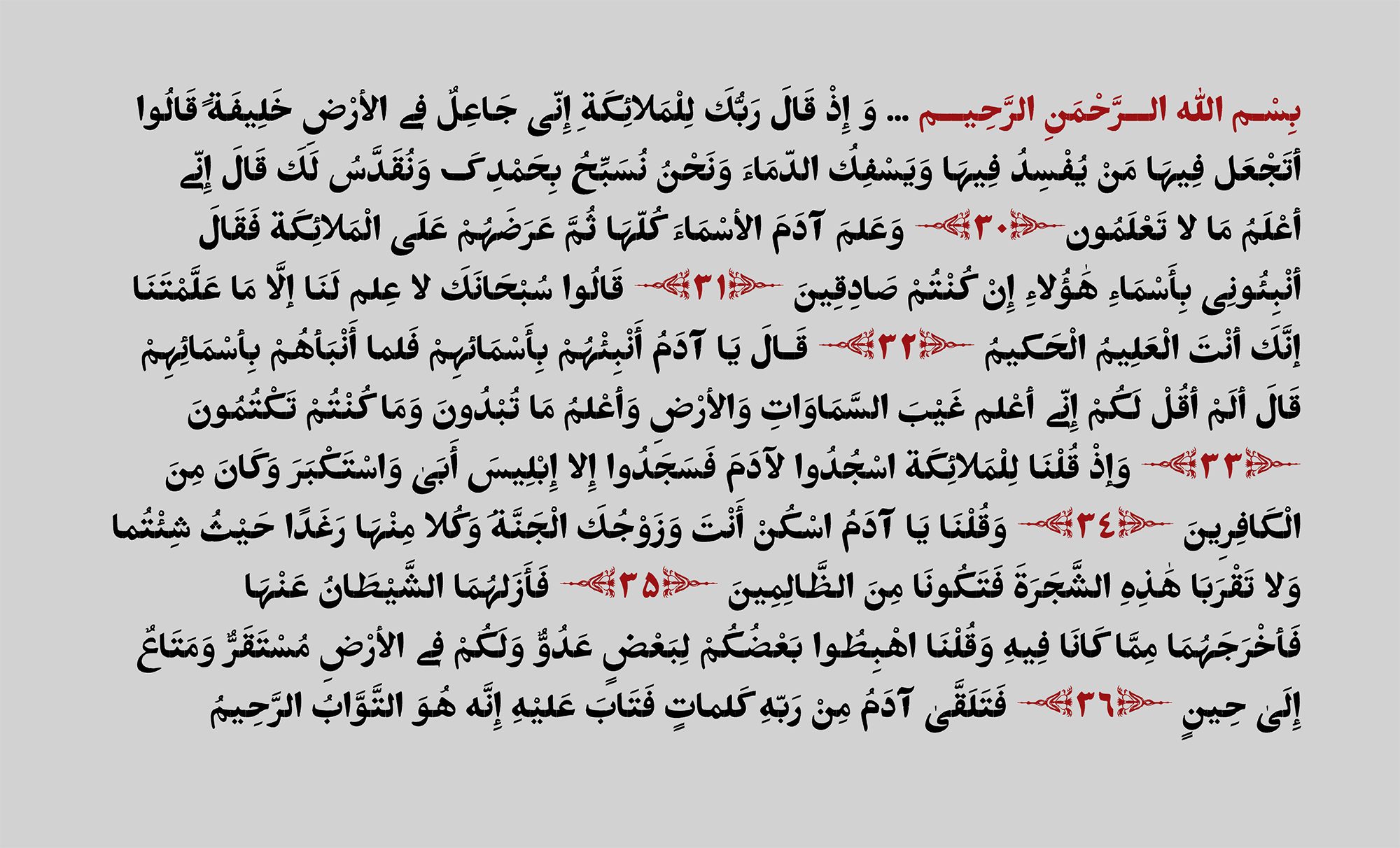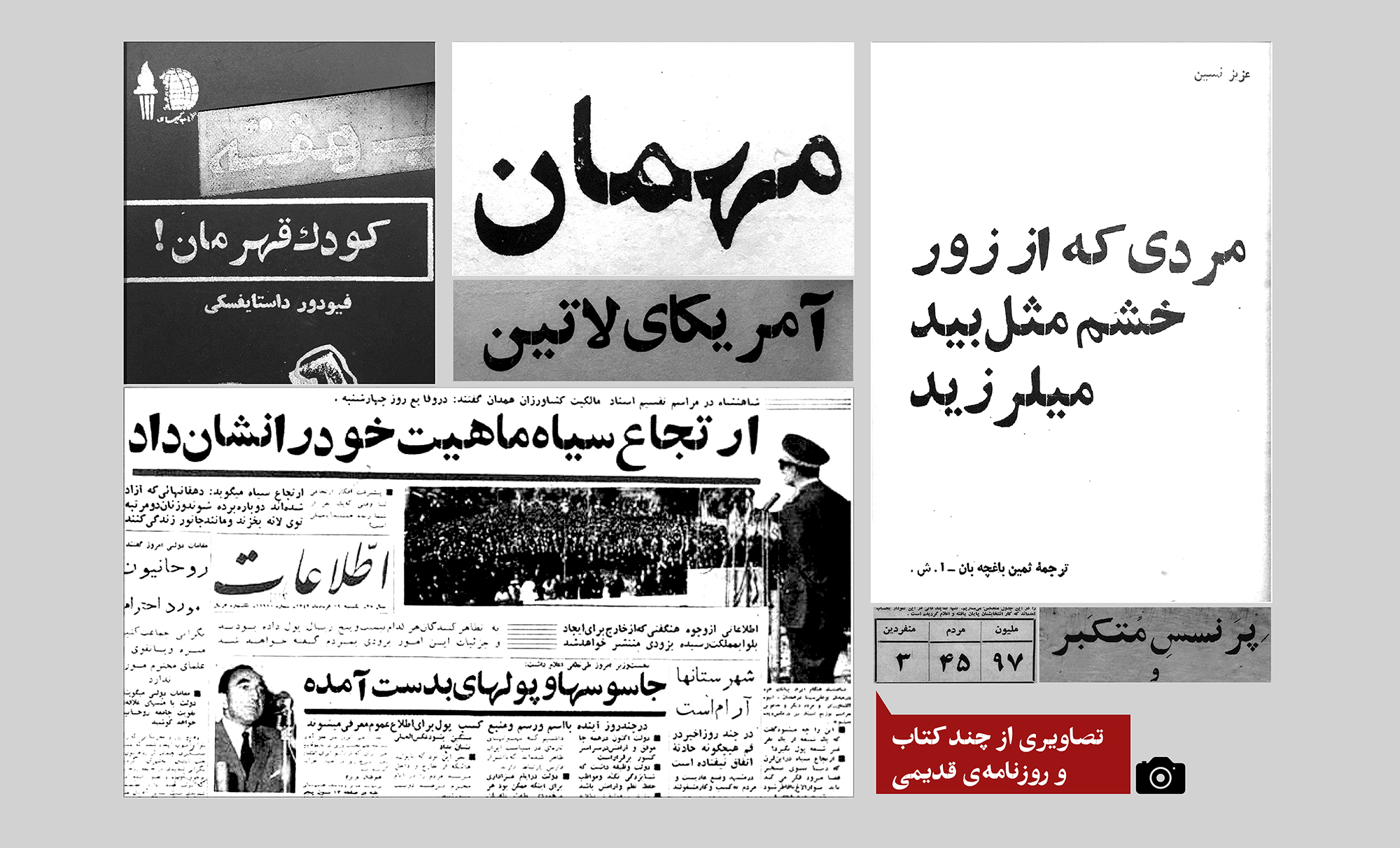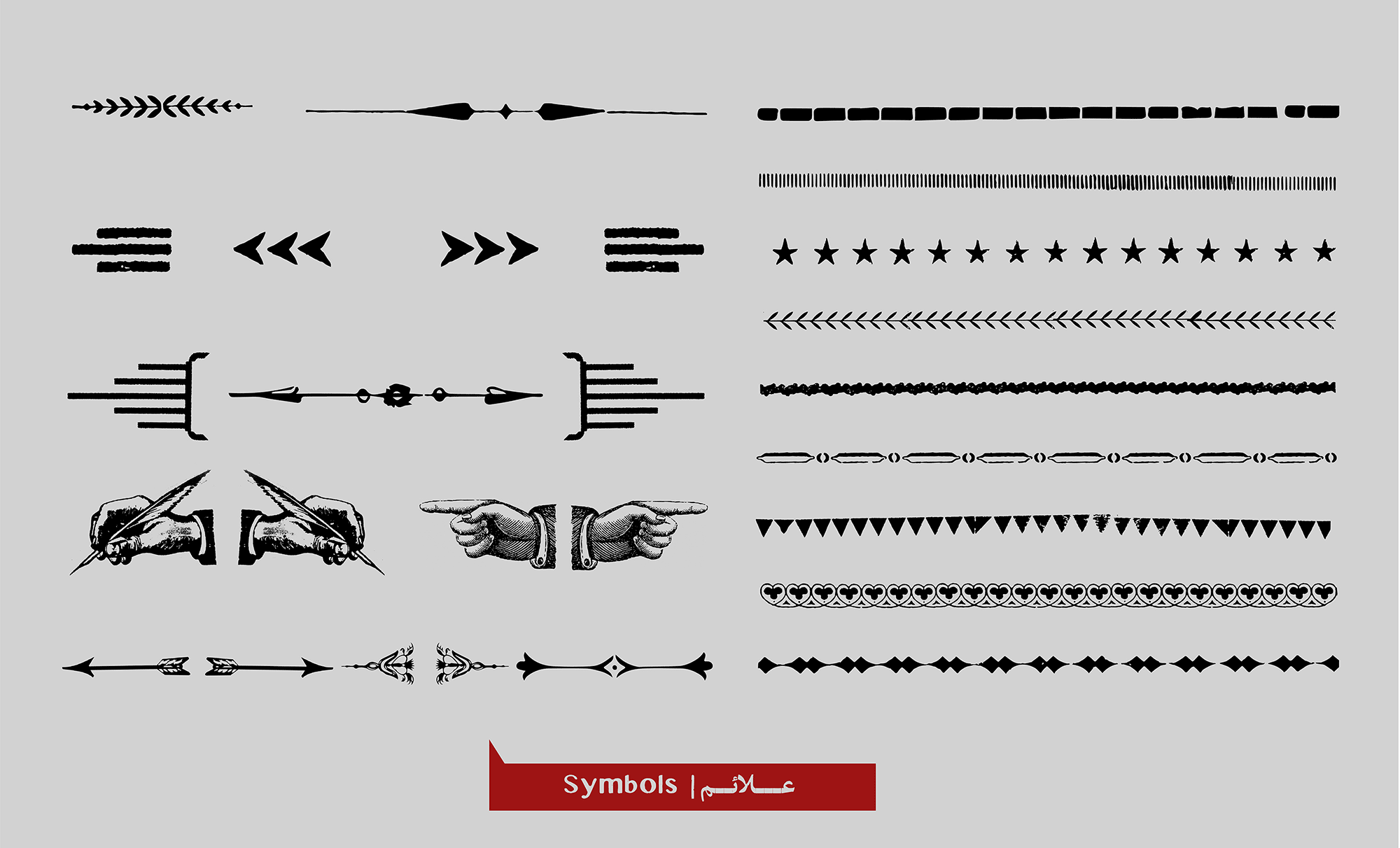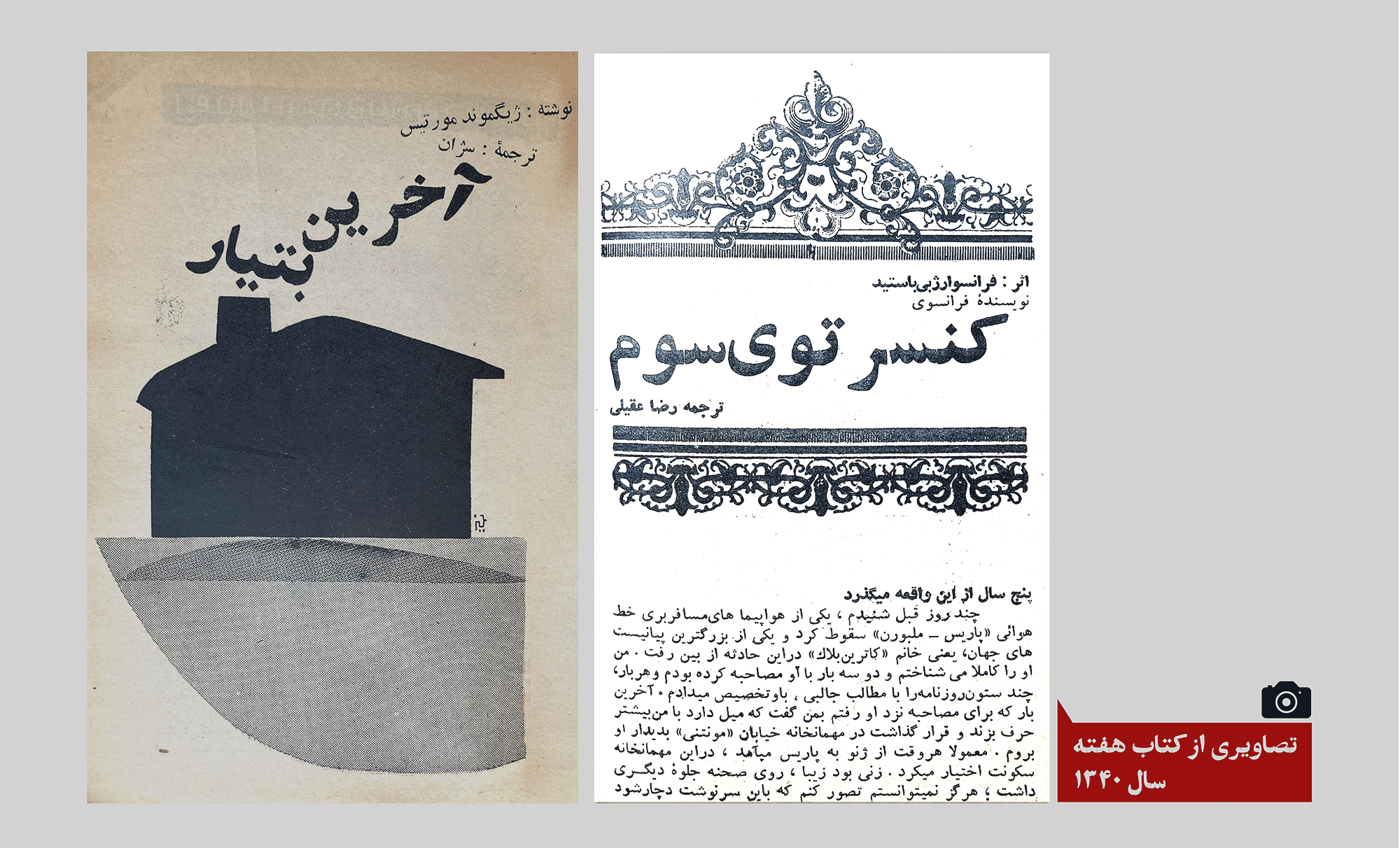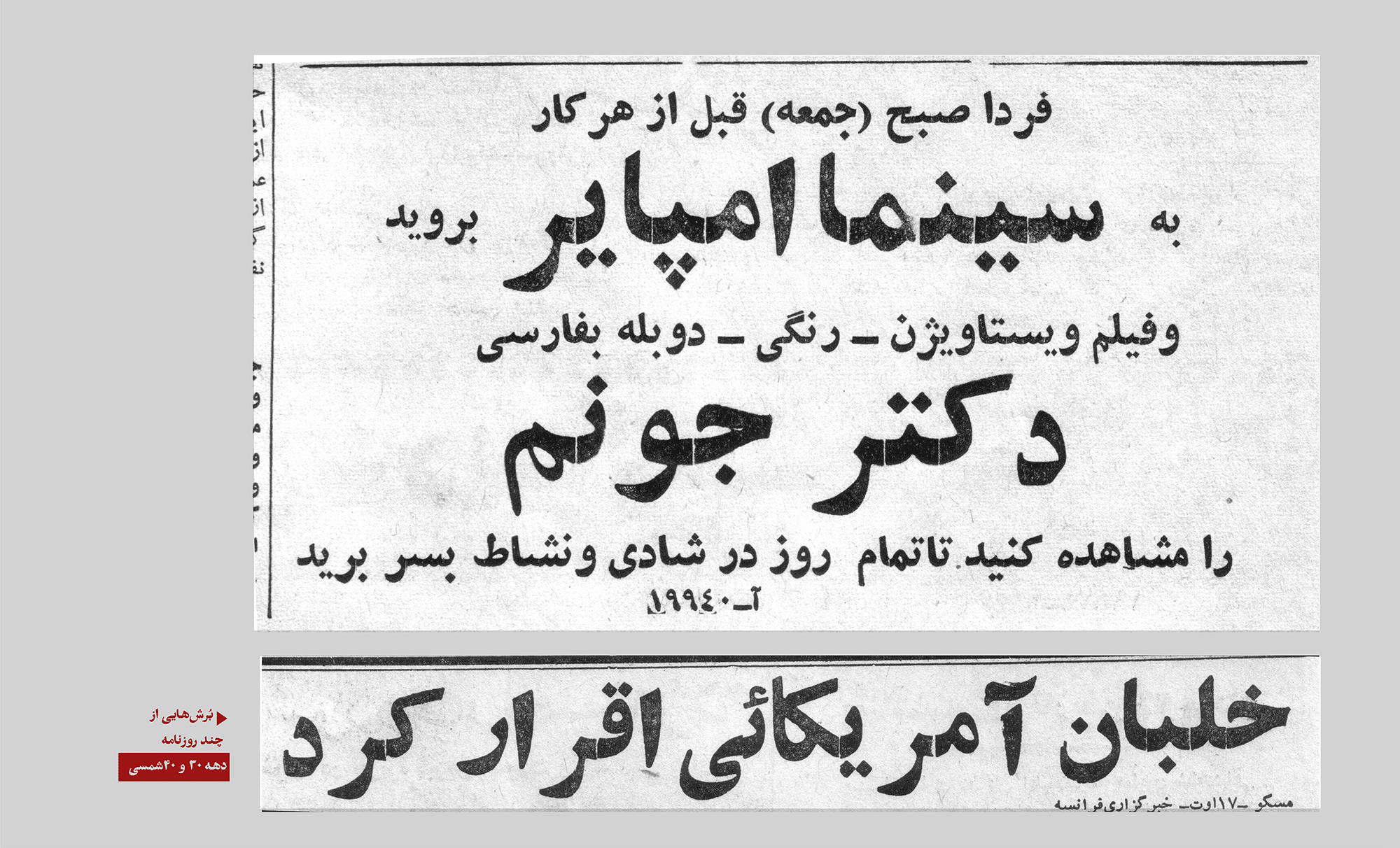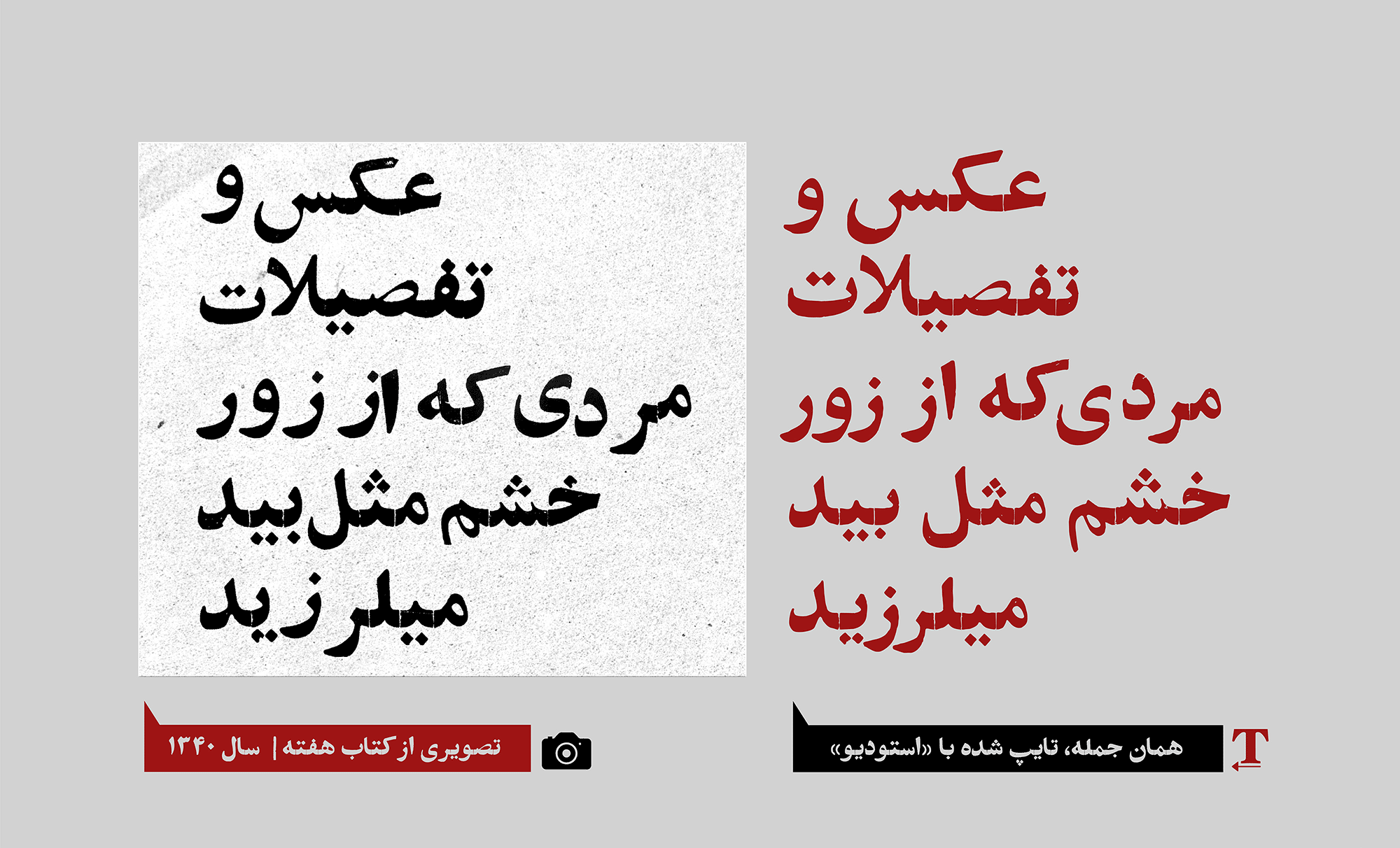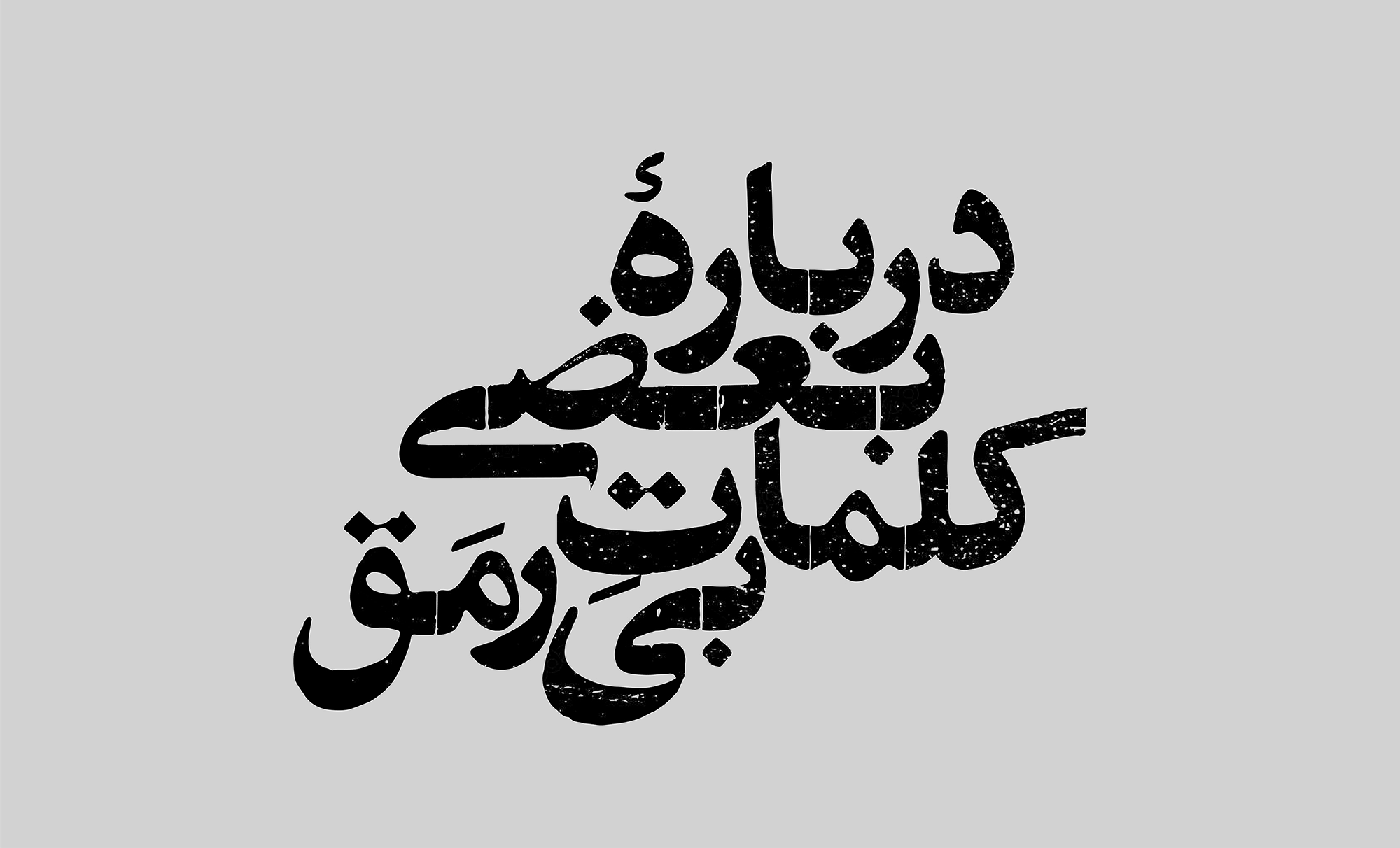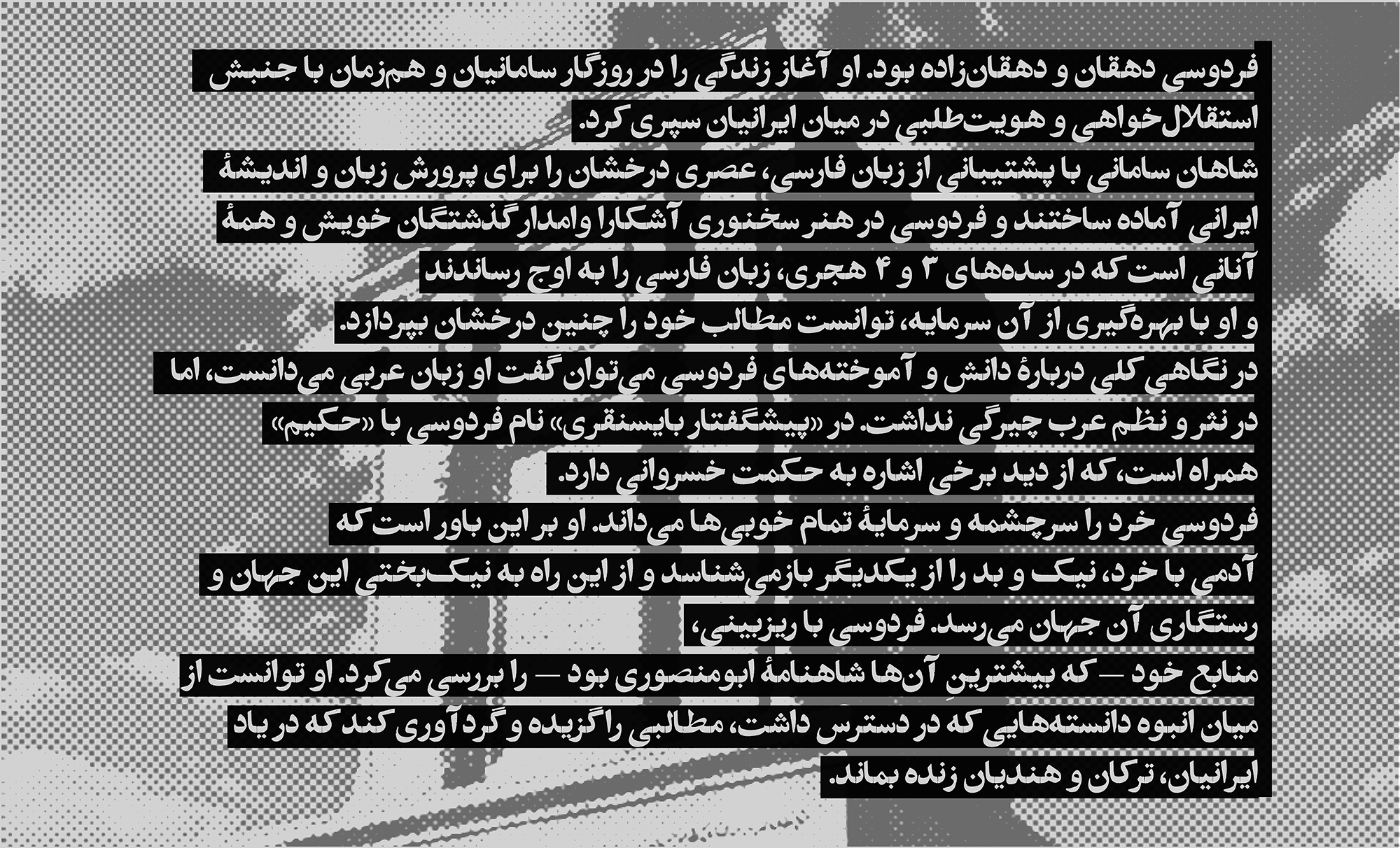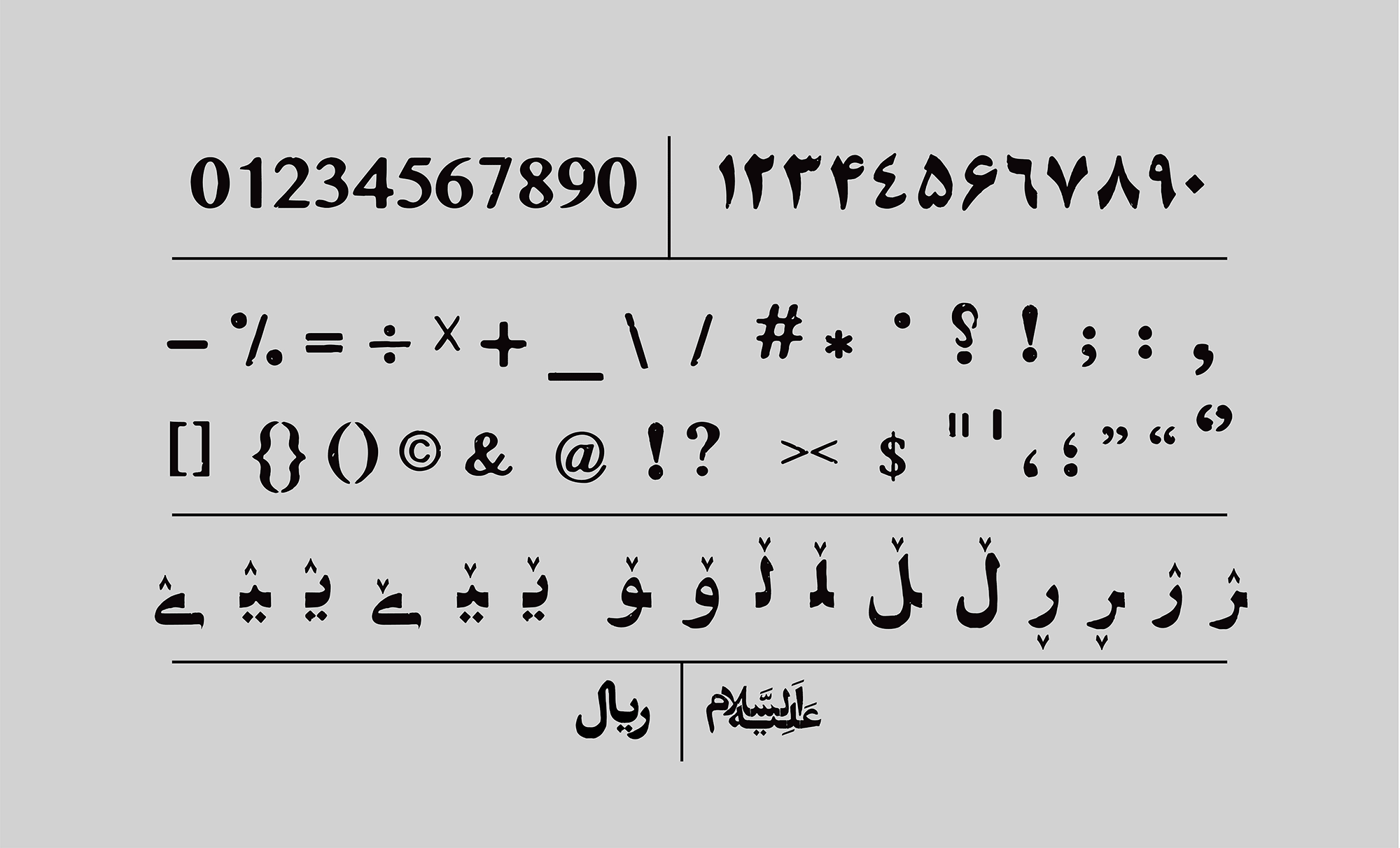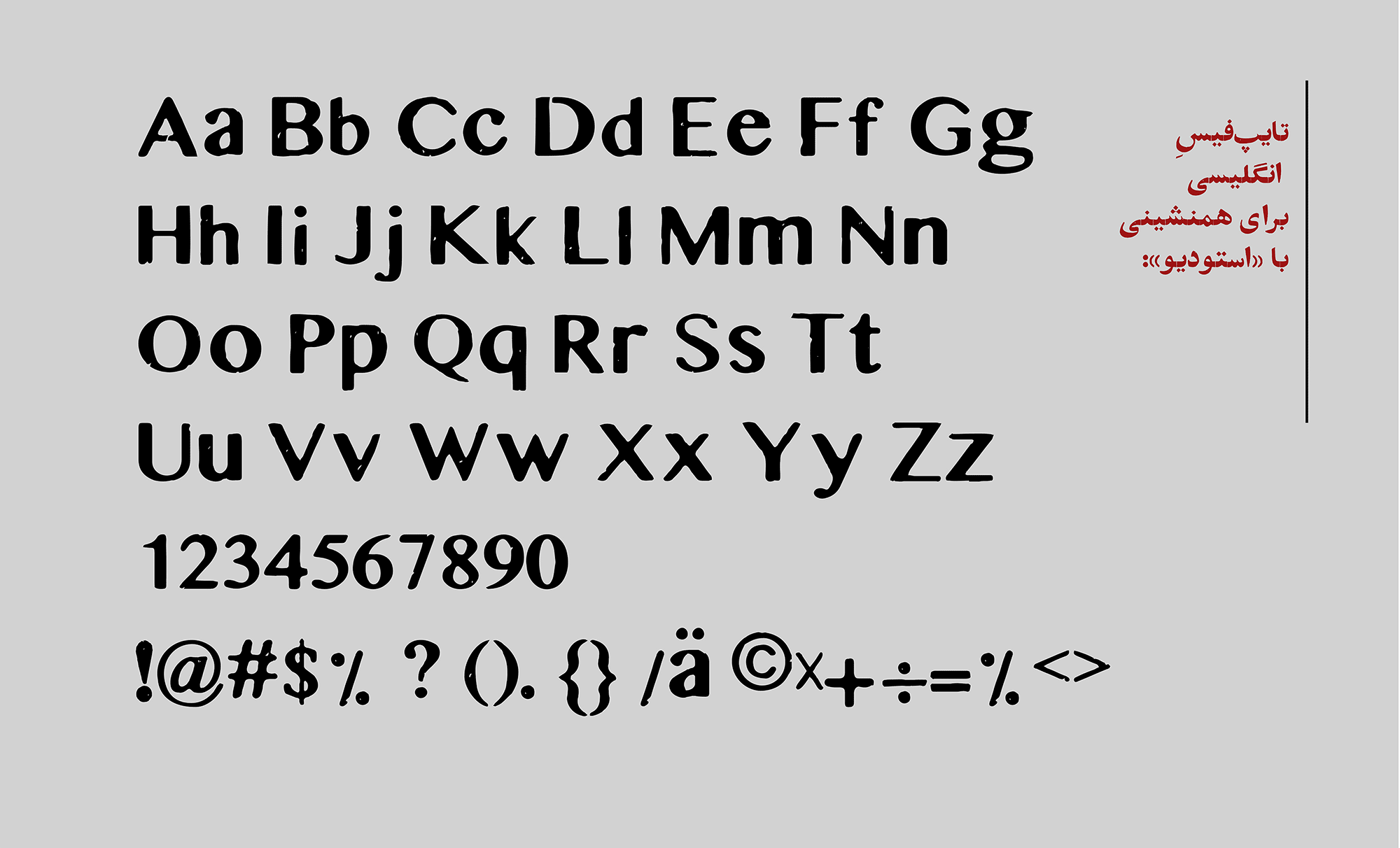
فونت استودیو در سه زبان فارسی، عربی و انگلیسی قابل استفاده است.
حروفِ تازهی کهنه!
طراحان گرافیک، طراحان فضای مجازی و وبسایت، ناشران، مطبوعات، طراحان صحنه، هنرمندان و همهی آنها که به نوعی با تایپفیسهای فارسی سروکار دارند، همواره با کمبودِ حروفی با حال وهوای قدیمی، برای ساخت فضاهای نوستالژیک مواجه هستند.
بههمین دلیل، هر وقت پای اِلقایِ حسّی قدیمی به کمک یک فونت به میان میآید، یا باید بیخیالش بشویم یا با دستکاریِ نمونههای موجود، عجالتاً کارمان را راه بیندازیم!
برشهایی از چند روزنامه و کتاب قدیمی
یک سابقه طولانی!
قدمت این فونت که امروز؛ با نام «استودیو» نامگذاری شده است؛ به روزنامهها، آگهیها و کتابهایی برمیگردد که حدود ۷۰ سال پیش به شیوهی «چاپ سُربی» منتشر میشدند. اوج استفاده از این حروف در دوران پهلوی بوده و هویت طرّاح احتمالی آن نامشخص است.
باخروج حروف سُربی از گردونۀ تولید، این فونت نیز رفتهرفته به محاق فراموشی رفت.
صفحاتی از مجلهی «کتاب هفته»- ۱۳۴۰
برشهایی از چند روزنامه / دهههای 30 و 40 شمسی
حفظ اصالت و هویت!
در طی مراحل بازسازی، به تغییر شکلی (دفرماسیون) که پروسهی چاپ سـربی با گذر زمان در ریخت حروف به وجـود میآورد وفادار بودیم. شکل حروف و اتصالات تناسب دقیقی با هم ندارند، بعـضی بهصورت صحیح بر روی خط کرسی قرار ندارند و تناسب و اندازهی حروفِ همسان لزوماً شبیه به یکدیگر نیست. در محیط و سطح حروف بافتها و خوردگیهایی مشاهده میشود که تلاش کردیم همه را حفظ کنیم. همچنین در نسخه نهایی، کاراکترهای اول، وسط، آخر و تنهای حروف، هر کدام شکل و بافتِ مختص به خود را دارند و اینطور نیست که مثلاً خانواده حروف «س» و «ش» تنها با اضافه کردن چند نقطه ساخته شده باشند.
وفاداری به منابع اصلی در جهت حفظ شباهت و ماهیت
بزرگ تا متوسط!
فونت استودیو با حفظ اصالت تصویری و پایبندی به منابع اصلی، به کمک اصلاحات و اضافه کردن امکانات جدید، نیازهای گوناگون شما را در فضای طراحی گرافیک، طراحی وب، فضای مجازی، طراحی تبلیغاتی، مطبوعاتی، کتابآرایی، طراحی هنری و… برآورده می کند. اگر چه بیشترین کاربردِ فونت استودیو در اندازههای بزرگ است، اما این فونت در حد فاصل اندازههای متوسط تا ترکیبات درشت، همچنان زیبایی، خاصبودن، خوانایی و وقار خود را حفظ میکند.
استودیوی عربی!
با پیشبینی اِعرابها و برخی ترکیبات خاص، فونت استودیو می تواند از متنهای به زبان عربی پشتیبانی کند.
اعداد/ علائم/ حروف کردی
همخانوادهی انگلیسی برای استودیو
تایپفیس انگلیسی که برای همنشینی با «استودیو» انتخاب شده است، پس از ایجاد خوردگی، بافت و تغییراتی در ترکیب، بیشترین شباهت را به همخانوادهی فارسیاش پیدا کرده تا در متون دوزبانه این جنس و شخصیت حروف متناسب و یکدست به نظر بیایند.
علائم و اَشکالِ کمکی / Symbols
در فرآیند تایپ کردن، با استفاده از علائمی که در جدول حروفِ فونت استودیو قرار داده شده ، میتوانید به جذابیت طراحی اضافه کنید.
فونت استودیو ؛ سال ۱۳۹۶ در استودیو دفتر و زیر نظر مجید کاشانی بازسازی، اصلاح و اجرا شد. تعداد زیادی روزنامه، کتاب، مجله و آگهیهای قدیمی، منابعی بودند که برای استخراج حروف و ترکیبات مورد استفاده قرار گرفتند. این فونت اولین بار برای مدتی محدود در سایت «اهدای عضو ایرانیان» عرضه شد و همه عواید مالی آن صرف درمان بیماران نیازمند پیوند عضو شد. سرانجام پس از وقفهای حدودا سه ساله، آبانماه ۱۴۰۰، در وبسایت «فونت ایران» عرضه شد.